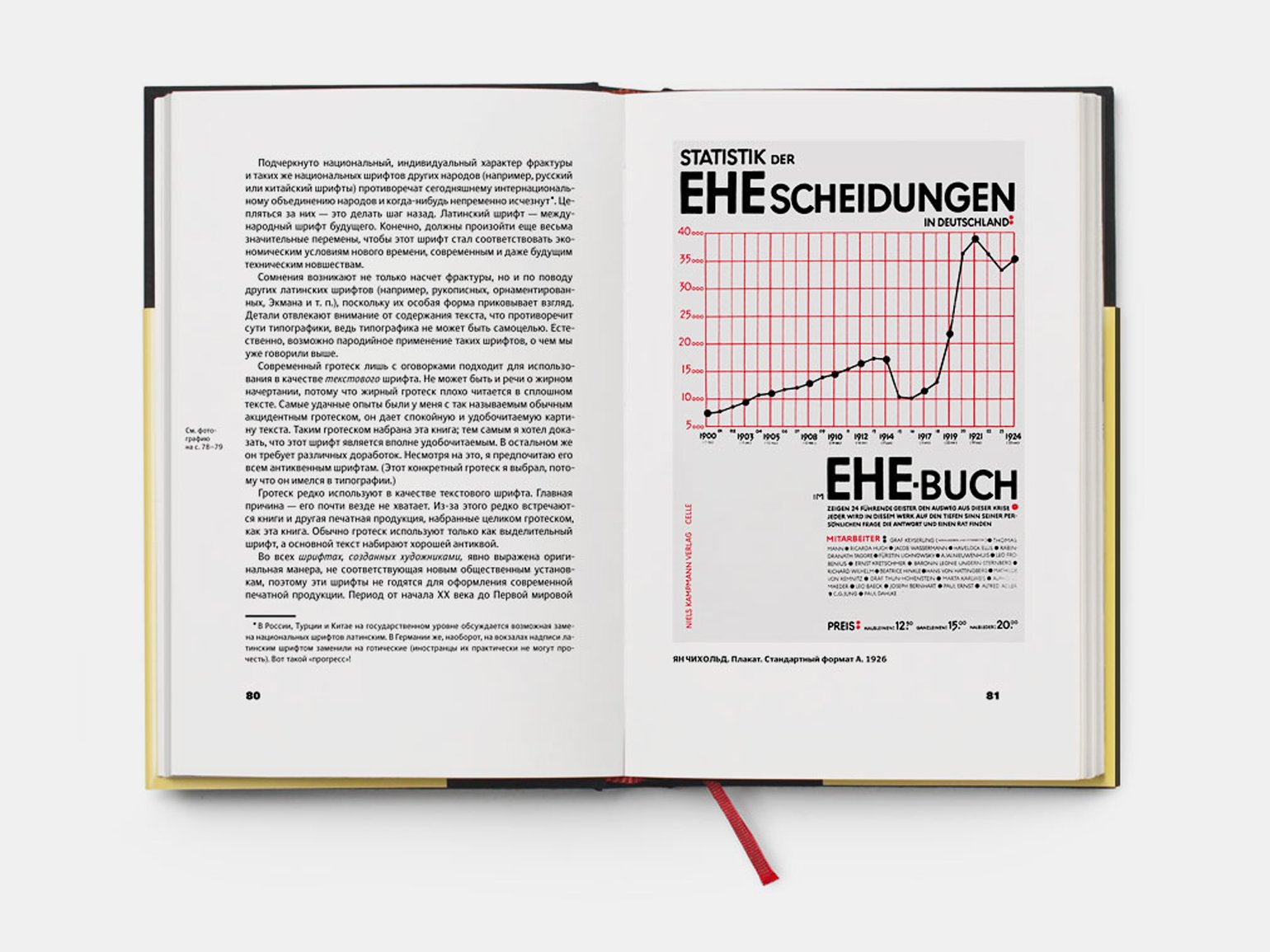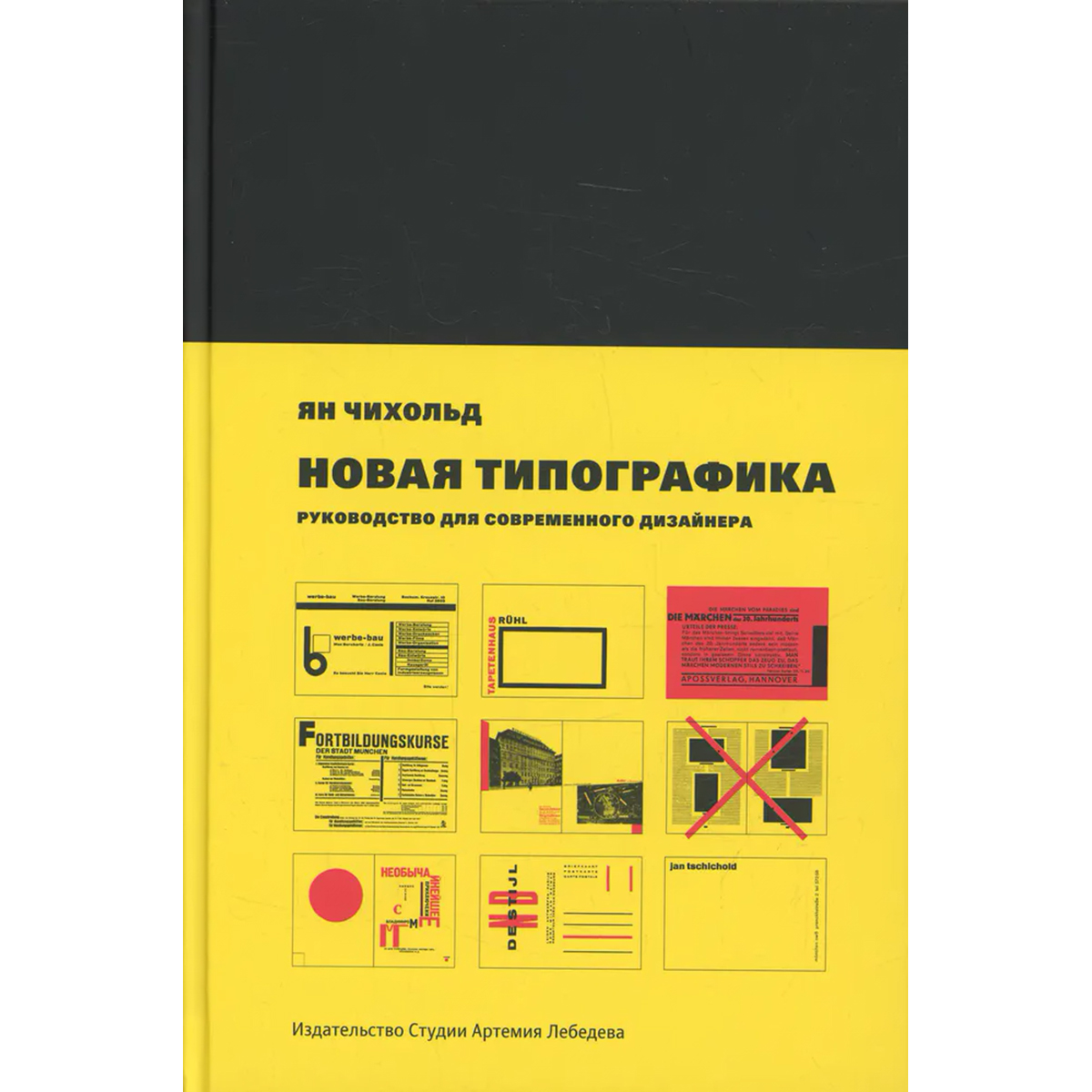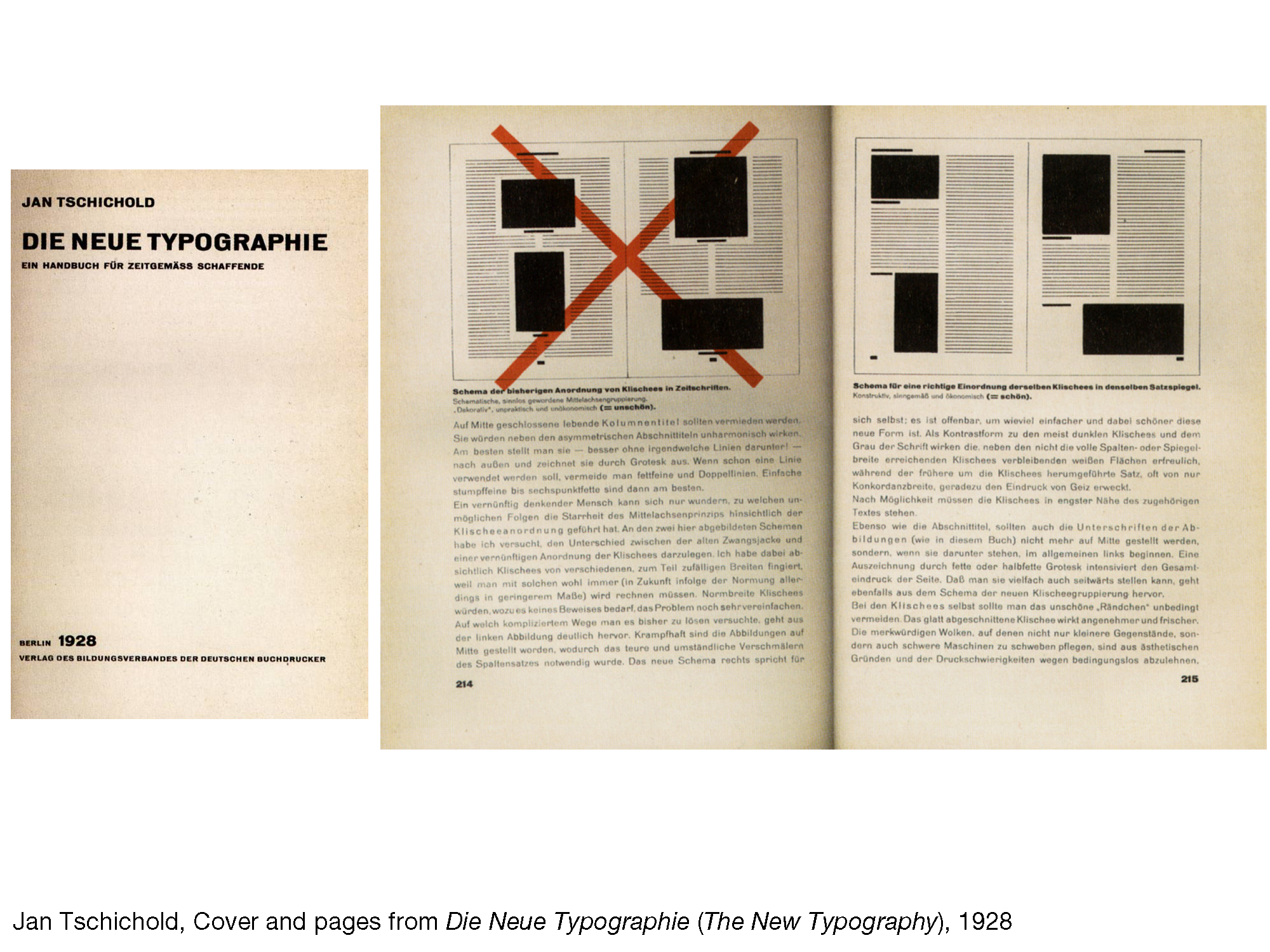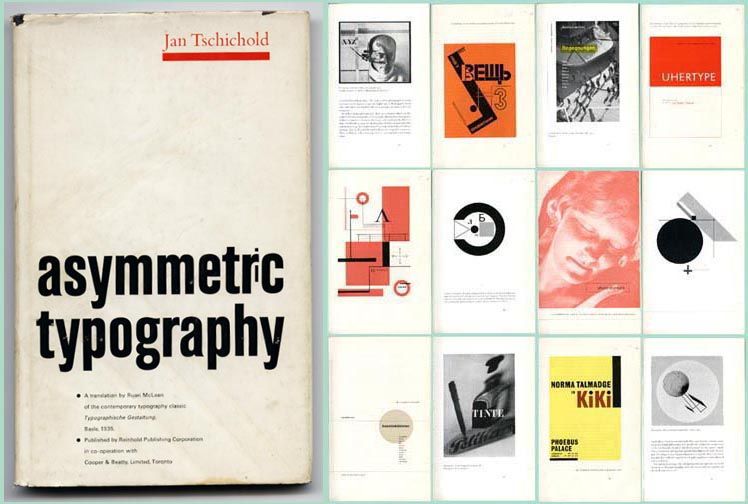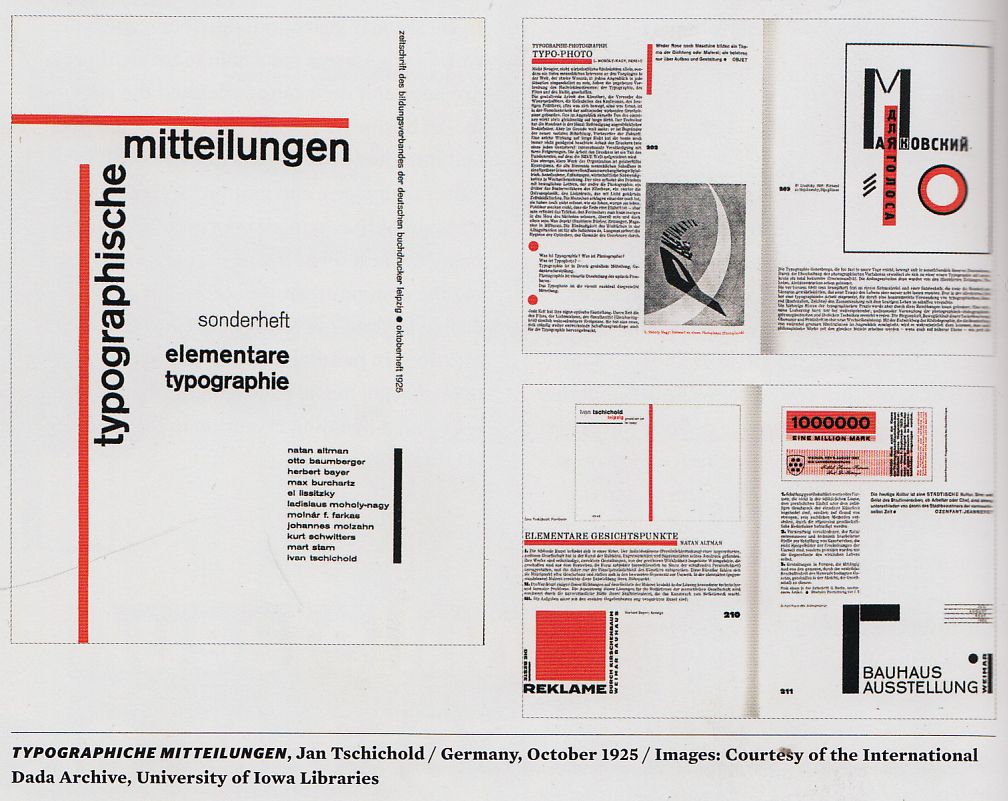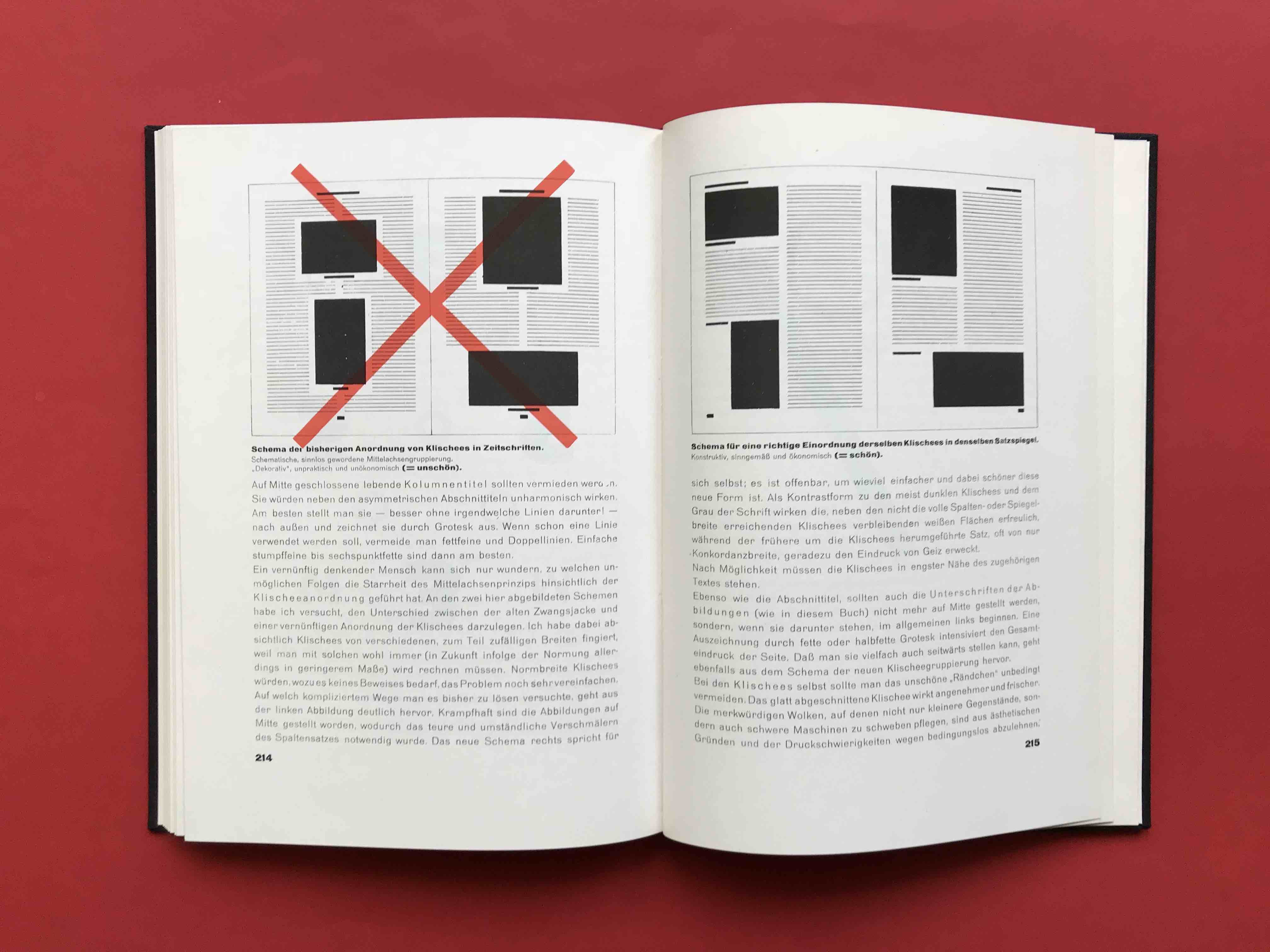
Отказ от личного тщеславия
Адаптация формы
Асимметрия
Убрать украшательства
Орнаменты транслируют наивное ребячество
Контраст как инструмент выделения
Цвет как элемент воздействия
Единый шрифт экономит деньги
Многообразие – результат произвола
То, что начиналось как экспериментальная тенденция среди художников-авангардистов, было адаптировано пехотинцами печатных СМИ в новый визуальный словарь для графической коммуникации. Кроме того, к 1930 это стало основным направлением коммерческого дизайна в Центральной Европе, появляясь в рекламе, журналах и особенно в фирменном стиле и рекламе промышленных корпораций. Нацисты, возможно, положили конец этому в Германии в 1933 году путем массовых арестов и увольнений, но его влияние как средства коммуникации, особенно в рекламе, было непоколебимо. В послевоенный период Новая типографика снова появилась как «швейцарский стиль», и в руках нового поколения дизайнеров, обученных принципам работ Яна Чихольда, этот подход доминировал в рекламном дизайне в западном мире на протяжении большей части двадцатого века.